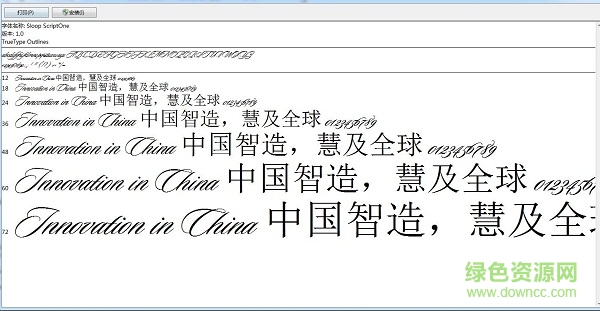
sloop字體是一款非常漂亮的花式英文手寫字體,線條結(jié)構(gòu)帶有花體字體的特征,風(fēng)格獨特,流暢美觀,可以用作裝飾字體或廣告字體使用,歡迎大家前來下載!
漂亮而優(yōu)雅的“花體字”,據(jù)說國外一般用在正式場合,感覺很有皇家風(fēng)范。
花體是“ornamental penmanship”的不當(dāng)翻譯,英文本意為裝飾性強(qiáng)的寫法,應(yīng)并不特指一種字體,一般粗細(xì)變化明顯,有如游絲。